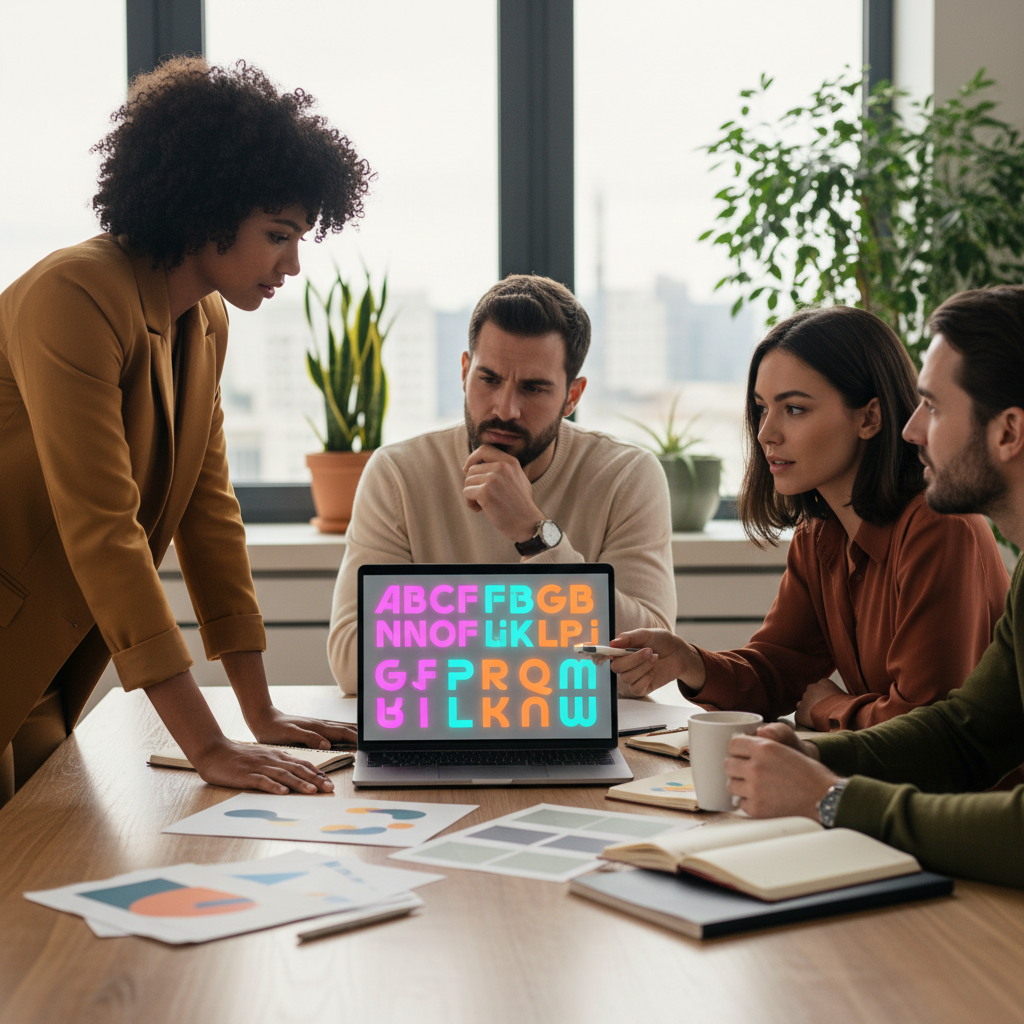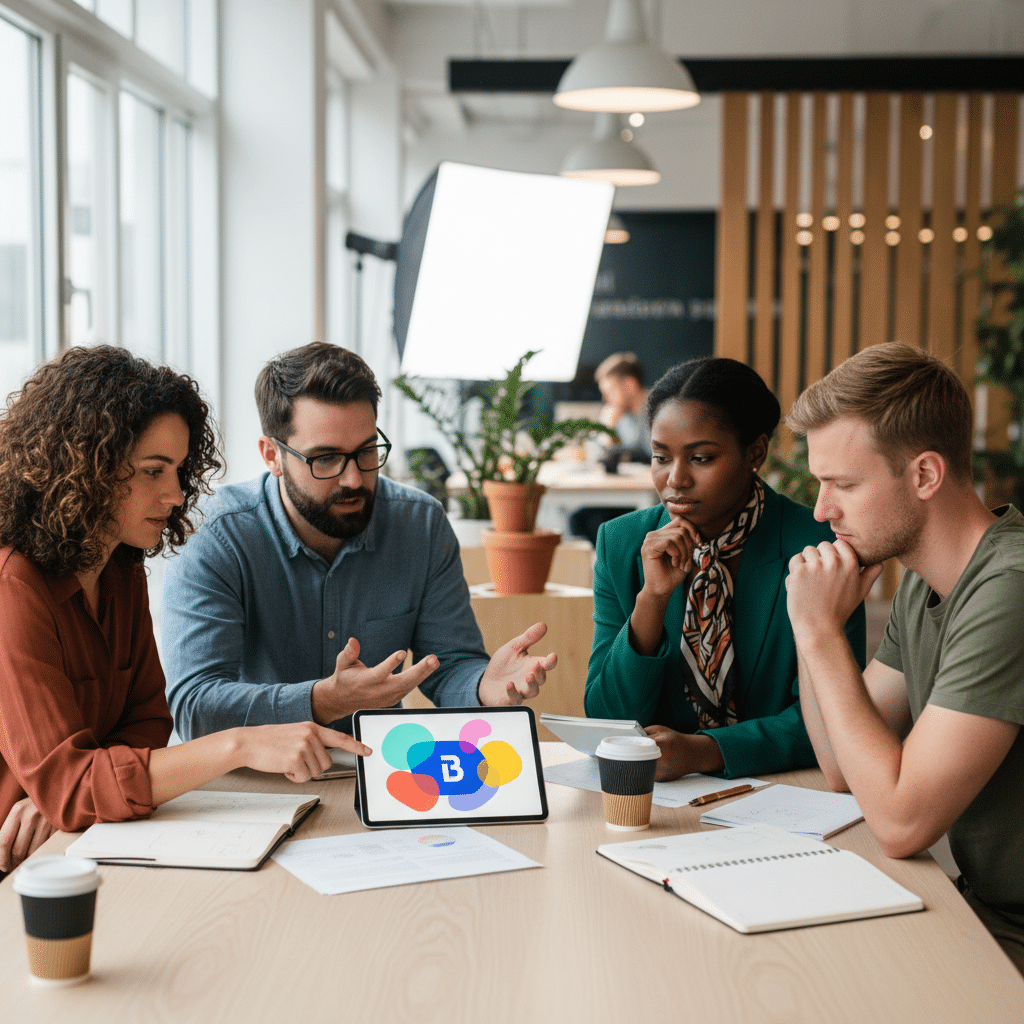
จิตวิทยาฟอนต์: เลือกใช้ให้เป็น เปลี่ยนแบรนด์ SME ให้ปัง
ในโลกธุรกิจที่มีการแข่งขันสูง การสร้างแบรนด์ให้เป็นที่จดจำคือหัวใจสำคัญสู่ความสำเร็จ ฟอนต์ หรือ รูปแบบตัวอักษร เป็นมากกว่าองค์ประกอบด้านการออกแบบ แต่เป็นเครื่องมือสื่อสารที่ทรงพลังซึ่งสามารถกำหนดการรับรู้และสร้างความรู้สึกร่วมกับแบรนด์ได้
- ฟอนต์ทำหน้าที่เป็น “เสียง” และ “บุคลิกภาพ” ของแบรนด์ สื่อสารตัวตนไปยังผู้บริโภคโดยไม่ต้องใช้คำพูด
- ฟอนต์แต่ละประเภท เช่น Serif, Sans Serif หรือ Script กระตุ้นการรับรู้และอารมณ์ที่แตกต่างกัน ตั้งแต่ความน่าเชื่อถือ ความทันสมัย ไปจนถึงความเป็นมิตร
- การเลือกฟอนต์ที่สอดคล้องกับธุรกิจ SME ช่วยเพิ่มความน่าเชื่อถือ สร้างความสัมพันธ์ และทำให้แบรนด์เป็นที่จดจำได้มากขึ้น
- การประยุกต์ใช้จิตวิทยาฟอนต์ครอบคลุมทุกส่วนของการสร้างแบรนด์ ตั้งแต่การออกแบบโลโก้ ฉลากสินค้า ไปจนถึงเว็บไซต์และสื่อโซเชียลมีเดีย
แก่นแท้ของจิตวิทยาฟอนต์
จิตวิทยาฟอนต์: เลือกใช้ให้เป็น เปลี่ยนแบรนด์ SME ให้ปัง คือแนวคิดที่ศึกษาความเชื่อมโยงระหว่างรูปแบบของตัวอักษร (Typography) กับการรับรู้ อารมณ์ และพฤติกรรมของมนุษย์ หลักการนี้ไม่ใช่เพียงเรื่องของความสวยงาม แต่เป็นศาสตร์และศิลป์ในการเลือกใช้ฟอนต์เพื่อสร้างอัตลักษณ์ที่ชัดเจนให้กับแบรนด์ โดยเฉพาะสำหรับธุรกิจขนาดกลางและขนาดย่อม (SME) ที่ทรัพยากรอาจมีจำกัด การเลือกฟอนต์ที่ถูกต้องจึงเป็นกลยุทธ์ต้นทุนต่ำที่สร้างผลกระทบได้อย่างมหาศาล ฟอนต์ที่เหมาะสมสามารถทำให้แบรนด์ดูน่าเชื่อถือ เป็นมืออาชีพ ทันสมัย หรือเข้าถึงง่าย ซึ่งจะส่งผลโดยตรงต่อการตัดสินใจของลูกค้าและสร้างความได้เปรียบในการแข่งขัน
เหตุผลที่ SME ต้องให้ความสำคัญกับการเลือกฟอนต์
สำหรับผู้ประกอบการ SME การสร้างแบรนด์ให้โดดเด่นท่ามกลางคู่แข่งจำนวนมากเป็นความท้าทายอันดับต้นๆ ฟอนต์คือหนึ่งในเครื่องมือที่สำคัญที่สุดในการสร้างภาพลักษณ์แรกพบ (First Impression) และสื่อสารตัวตนของแบรนด์ออกไปอย่างมีประสิทธิภาพ การลงทุนเวลาเพื่อทำความเข้าใจและเลือกฟอนต์ที่ใช่จึงไม่ใช่เรื่องเล็กน้อย แต่เป็นการวางรากฐานที่แข็งแกร่งให้กับแบรนด์ในระยะยาว
การสร้างบุคลิกภาพและความแตกต่าง
ฟอนต์เปรียบเสมือน “เสื้อผ้า” ที่แบรนด์สวมใส่ มันสามารถบอกเล่าเรื่องราวและกำหนดบุคลิกภาพของแบรนด์ได้ทันที แบรนด์ที่ปรึกษาทางการเงินอาจเลือกใช้ฟอนต์ที่ดูมั่นคง จริงจัง และน่าเชื่อถือ ในขณะที่ร้านกาแฟสไตล์มินิมอลอาจเลือกใช้ฟอนต์ที่ดูสะอาดตา เป็นมิตร และทันสมัย การเลือกฟอนต์ที่แตกต่างและสอดคล้องกับตัวตน จะช่วยให้แบรนด์ของคุณโดดเด่นและเป็นที่จดจำในใจของผู้บริโภค
การสื่อสารค่านิยมของแบรนด์
นอกเหนือจากบุคลิกภาพแล้ว ฟอนต์ยังสามารถสื่อสารค่านิยมหลัก (Core Values) ขององค์กรได้อีกด้วย แบรนด์ที่เน้นนวัตกรรมและความล้ำสมัยมักจะใช้ฟอนต์กลุ่ม Sans Serif ที่เรียบง่ายและสะอาดตา ส่วนแบรนด์ที่เน้นเรื่องประวัติศาสตร์อันยาวนานและความเป็นต้นตำรับ อาจเลือกใช้ฟอนต์กลุ่ม Serif ที่ให้ความรู้สึกคลาสสิกและภูมิฐาน การสื่อสารที่สอดคล้องกันนี้จะช่วยสร้างความไว้วางใจและทำให้ลูกค้ารู้สึกเชื่อมโยงกับแบรนด์ได้ลึกซึ้งยิ่งขึ้น
ผลกระทบจากการเลือกฟอนต์ที่ไม่เหมาะสม
ในทางกลับกัน การเลือกฟอนต์ที่ไม่เหมาะสมอาจส่งผลเสียต่อภาพลักษณ์ของแบรนด์ได้อย่างไม่น่าเชื่อ การใช้ฟอนต์ที่ดูสนุกสนานและไม่เป็นทางการกับแบรนด์ที่ต้องการความน่าเชื่อถือสูง เช่น สถาบันการเงินหรือคลินิกสุขภาพ อาจทำให้ลูกค้าเกิดความไม่มั่นใจและมองว่าแบรนด์ขาดความเป็นมืออาชีพ ในทำนองเดียวกัน การใช้ฟอนต์ที่อ่านยากบนฉลากสินค้าหรือเว็บไซต์ อาจสร้างประสบการณ์ที่ไม่ดีและทำให้ลูกค้าเปลี่ยนใจไปเลือกซื้อสินค้าจากคู่แข่งได้
เจาะลึกประเภทฟอนต์และผลกระทบทางจิตวิทยา
การทำความเข้าใจลักษณะและ “บุคลิก” ของฟอนต์แต่ละประเภท เป็นก้าวแรกที่สำคัญในการเลือกใช้ให้เหมาะสมกับแบรนด์ โดยทั่วไป สามารถแบ่งฟอนต์ออกเป็นกลุ่มหลักๆ ได้ดังนี้
ฟอนต์มีเชิง (Serif): ความคลาสสิกที่น่าเชื่อถือ
ฟอนต์ประเภท Serif มีลักษณะเด่นคือมี “ขา” หรือ “เชิง” (Serif) เล็กๆ อยู่ที่ปลายเส้นของตัวอักษร ซึ่งช่วยนำสายตาทำให้อ่านข้อความยาวๆ ได้ง่ายในสื่อสิ่งพิมพ์ ฟอนต์กลุ่มนี้ให้ความรู้สึกเป็นทางการ, คลาสสิก, สง่างาม, น่าเชื่อถือ และสื่อถึงประวัติศาสตร์อันยาวนาน จึงมักถูกใช้โดยแบรนด์ที่ต้องการสร้างภาพลักษณ์ที่มั่นคงและมีคุณภาพสูง
- บุคลิก: ดั้งเดิม, ภูมิฐาน, เป็นทางการ, น่าเชื่อถือ, สง่างาม
- เหมาะกับธุรกิจ: สถาบันการเงิน, สำนักพิมพ์, แบรนด์แฟชั่นหรู, สำนักงานกฎหมาย, มหาวิทยาลัย, ธุรกิจที่เน้นความเป็นมืออาชีพและประสบการณ์
- ตัวอย่างแบรนด์: ROLEX, VOGUE, GUCCI, The New York Times
ฟอนต์ไม่มีเชิง (Sans Serif): ความเรียบง่ายทันสมัย
“Sans” เป็นภาษาฝรั่งเศสแปลว่า “ปราศจาก” ดังนั้นฟอนต์ Sans Serif จึงหมายถึงฟอนต์ที่ไม่มีเชิงที่ปลายอักษร ทำให้มีรูปลักษณ์ที่ดูสะอาดตา เรียบง่าย และทันสมัย ฟอนต์กลุ่มนี้ได้รับความนิยมอย่างสูงในสื่อดิจิทัล เนื่องจากอ่านง่ายบนหน้าจอที่มีความละเอียดแตกต่างกัน และสื่อถึงความตรงไปตรงมา เข้าถึงง่าย และความเป็นปัจจุบัน
- บุคลิก: ทันสมัย, เรียบง่าย, สะอาด, เป็นมิตร, ตรงไปตรงมา
- เหมาะกับธุรกิจ: บริษัทเทคโนโลยี, สตาร์ทอัพ, แบรนด์เสื้อผ้าสตรีทแวร์, ธุรกิจที่เน้นนวัตกรรมและความเรียบง่าย
- ตัวอย่างแบรนด์: Google, Microsoft, Facebook, Spotify
ฟอนต์สแลบเซริฟ (Slab Serif): ความแข็งแกร่งและมั่นใจ
ฟอนต์ Slab Serif เป็นลูกผสมระหว่าง Serif และ Sans Serif โดยมีเชิงที่หนาและเป็นรูปทรงสี่เหลี่ยมคล้ายแผ่นคอนกรีต (Slab) ทำให้ตัวอักษรดูหนา หนักแน่น และโดดเด่น ฟอนต์ประเภทนี้สื่อถึงความแข็งแกร่ง, ความมั่นคง, ความกล้าหาญ และความมั่นใจ มักถูกใช้เพื่อดึงดูดความสนใจและสร้างความรู้สึกที่ทรงพลัง
- บุคลิก: แข็งแกร่ง, มั่นใจ, โดดเด่น, กล้าหาญ, ทนทาน
- เหมาะกับธุรกิจ: อุตสาหกรรมยานยนต์, สินค้าเกี่ยวกับกิจกรรมกลางแจ้ง, แบรนด์ที่ต้องการสื่อถึงความแข็งแรงทนทาน